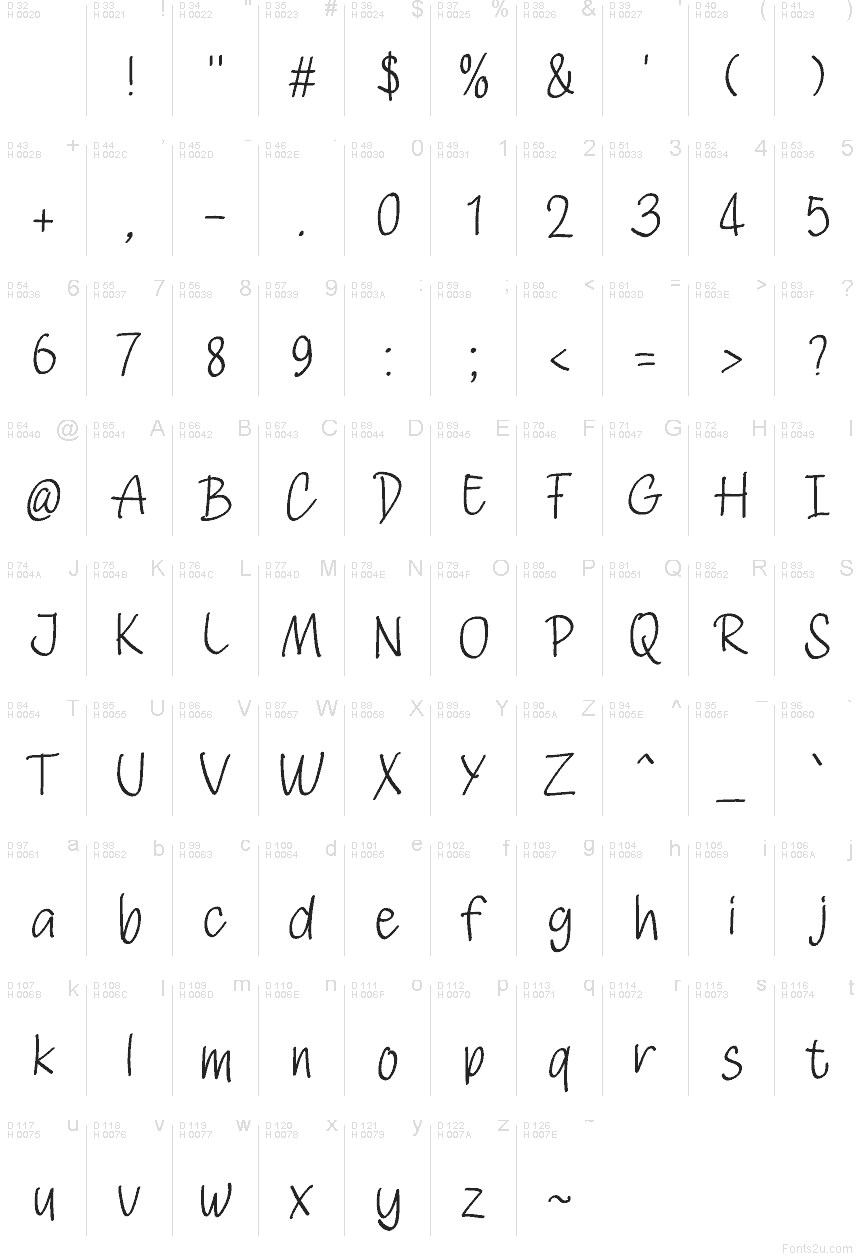
Unpackhand
Unpackhand é uma fonte manuscrita gratuita com um ritmo solto e natural, apresentando letras estreitas e ligeiramente irregulares. Os traços mantêm um toque humano e casual, com curvas abertas e formas fluidas que fazem o texto parecer escrito rapidamente, em vez de cuidadosamente construído.
Unpackhand funciona muito bem em convites, logotipos, embalagens, frases para redes sociais e cartões de felicitações, pois traz uma nota pessoal sem parecer decorativa de forma excessiva. Esta fonte gratuita também se adapta bem a cartazes curtos, gráficos para blogs e branding com estilo de assinatura, onde um script feito à mão transmite a mensagem com um toque simples e direto.